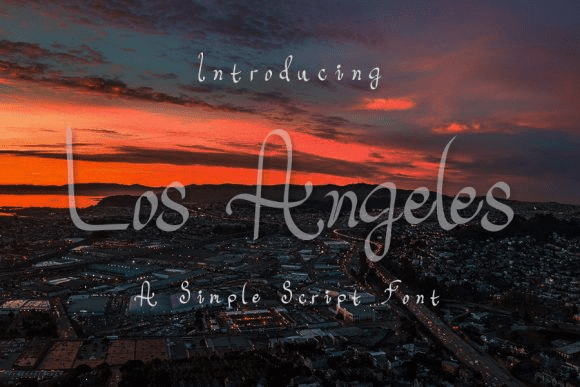
Название: Los Angeles Font
Лос-Анджелес - это стильный и невероятно элегантный шрифт сценария.
Он выглядит потрясающе на свадебных приглашениях, благодарственных открытках, цитатах, поздравительных открытках, логотипах, визитках и любом другом дизайне, который нуждается в рукописном прикосновении.